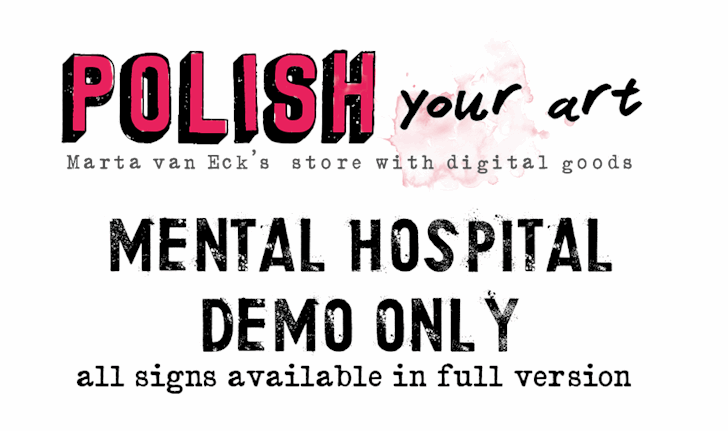
Mental Hospital Font – Fonte Grátis
Mental Hospital Font
A fonte Mental Hospital é uma criação única do designer Hamilton, projetada no estilo sombrio e desorganizado característico dos ambientes hospitalares psicossomáticos. Suas linhas grossas e suaves combinam elementos de arte cinza com elementos artesanais, ideal para adicionar um toque oscuro e carregado a qualquer design. Esta font é especialmente indicada para créditos em filmes de terror ou outros projetos que buscam criar uma atmosfera sombria e intensa. Um aspecto interessante dessa fonte é seu formato demonstrativo, o que permite visualizá-la sem comprometer os direitos autorais. Este modelo gratuito inclui apenas letras maiúsculas, mas todos os sinais estão disponíveis no formato completo para uso em projetos mais aprofundados. Se você está interessado em adquirir uma licença de uso comercial (para um único usuário), é importante notar que é necessário fazer um pedido através do endereço  e pagar $6. Para usuários finais, especialmente aqueles com interesses artísticos ou de design, é sempre recomendável verificar as condições específicas de uso das fontes disponíveis. Para maiores detalhes ou qualquer dúvida, Hamilton está disponível para contatar diretamente.